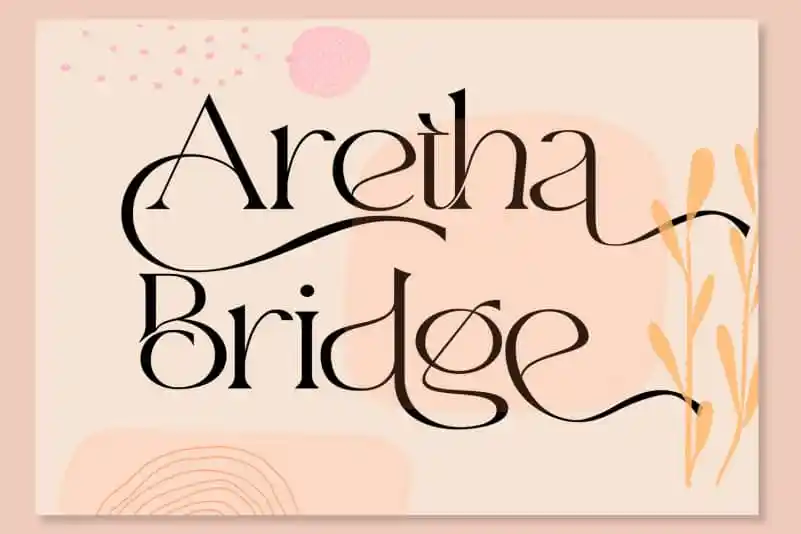
Aretha Bridge Serif Font – Download Grátis
Introduzimos a Aretha Bridge Serif Font, uma elegante fórmula serifada com uma personalidade moderna e sofisticada. Esta fonte vem equipada com ligaturas dispostas arbitrariamente para lhe oferecer todas as ferramentas necessárias para um tipo de alta qualidade. A Aretha Bridge é uma fonte que vai capturar o seu público, ajudando-o a destacar seus promotores e projetos. Viva sua marca em vida, e adicione um toque moderno e elegância com Aretha Bridge. Use-a nos títulos, logotipos, cartões de visita, cotações impressas, convites para todos os tipos, cartas, embalagens, ou mesmo o seu branding web ou redes sociais.